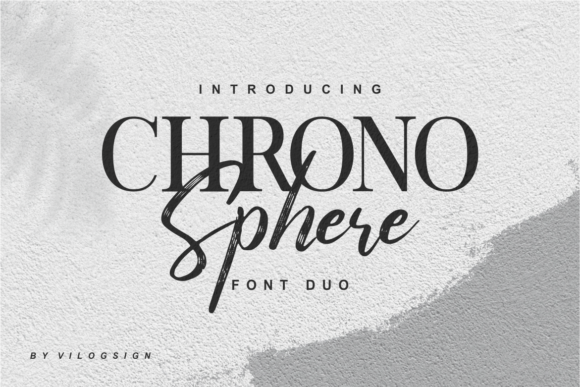
Chrono Sphere Font Duo – Download Grátis
A Chrono Sphere Font Duo é uma paixão para designers que desejam dar um toque sofisticado e elegante a suas criações. Esta dupla de fóntes serifas e script, criada pelo designer Vilogsign e compartilhada pela Zziplex, oferece um padrão único e luxuoso capaz de enriquecer qualquer projeto gráfico. Ideal para aplicações como cartões de convite, marcas de marca, cartelas de negócios, citações, panfletos e até mesmo logotipos ou revistas. A Chrono Sphere é especialmente adequada para uso em cartas de casamento, onde sua elegância se destacará. Seja para dar um toque sofisticado a qualquer projeto visual, seja ele um cartão de cumprimentos pessoal ou uma criação de marca completa. Essa fóntes proporcionará aos seus designs um brilho e uma qualidade premium que certamente impressionarão os olhos do público. Ainda mais incrível é a flexibilidade deste conjunto de fontes: pode-se misturar e combinar estas belas fóntes para criar design único em qualquer projeto. Seja qual seja o seu objetivo, seja ele uma marca pessoal ou profissional, ou uma publicação online, essa dupla de fóntes será perfeita. Você está pronto para usar a Chrono Sphere Font Duo?